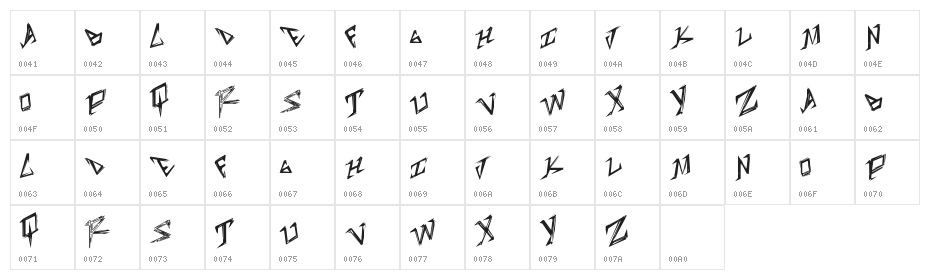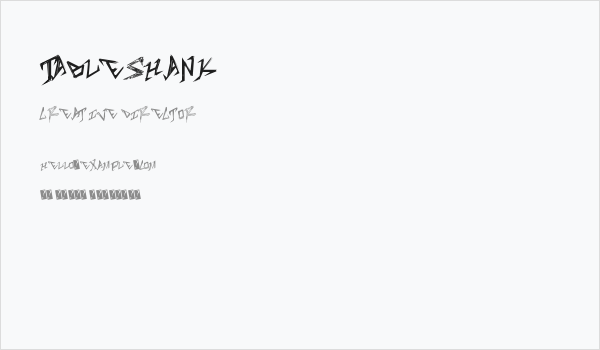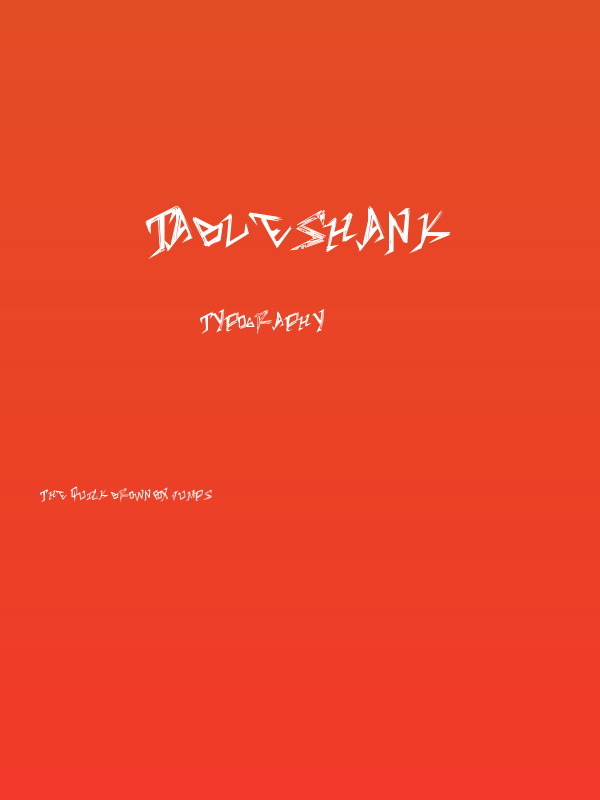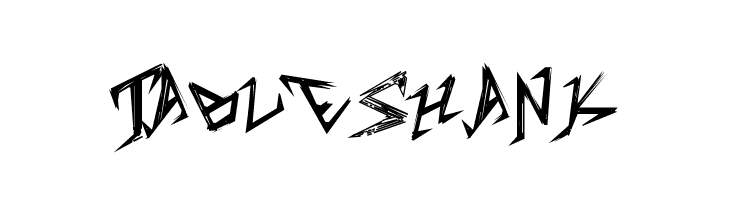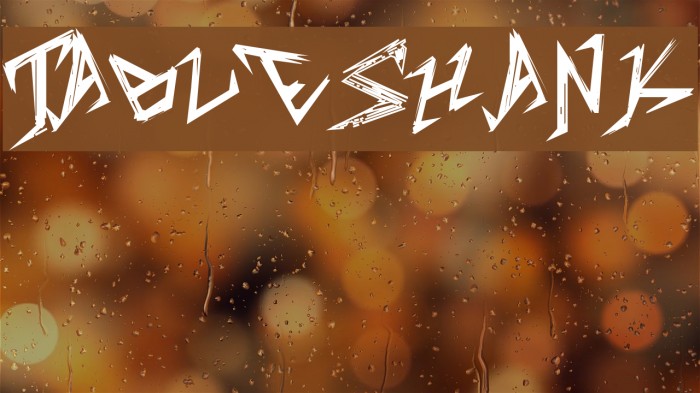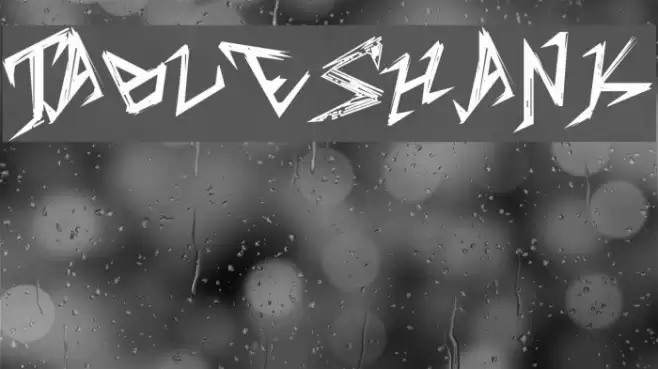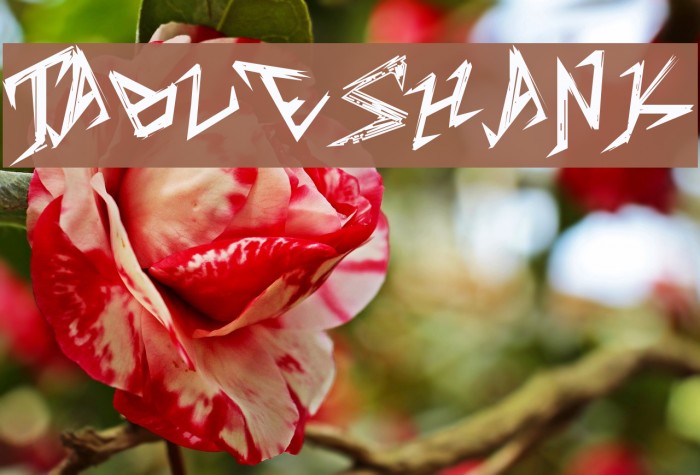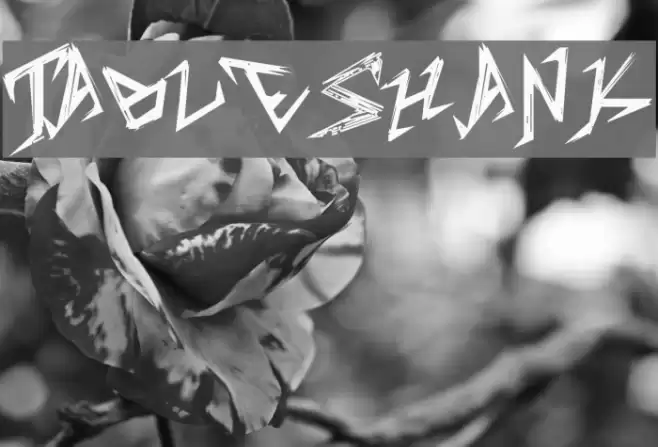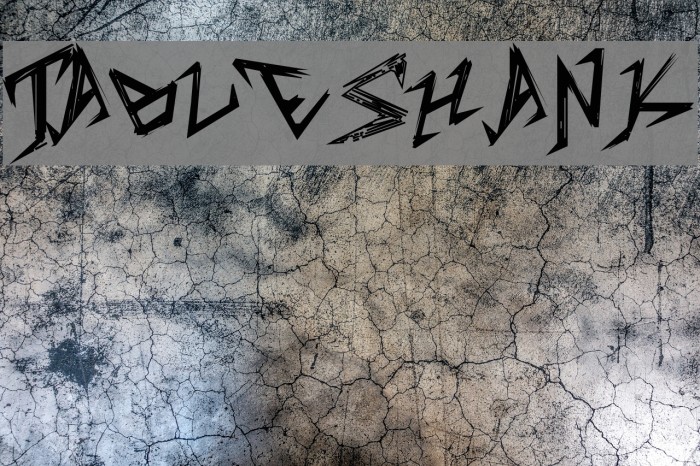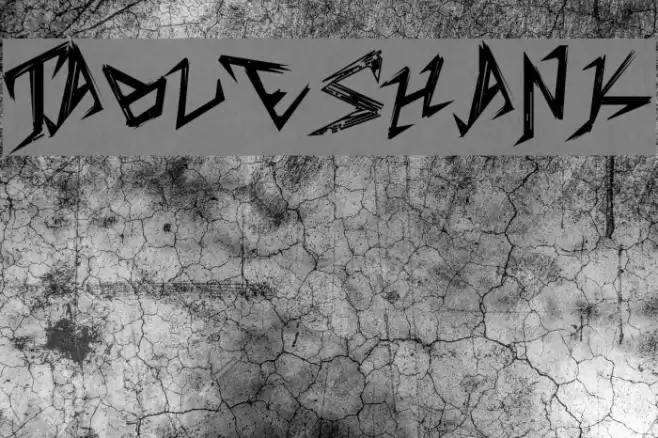
TableShank Font
| Estilo geral | Modern, Edgy |
| Caso de uso | Logos, Posters, Headlines |
| Projetos propostos | Ideal for music album covers, skateboarding brands, graffiti art, and edgy fashion labels. |